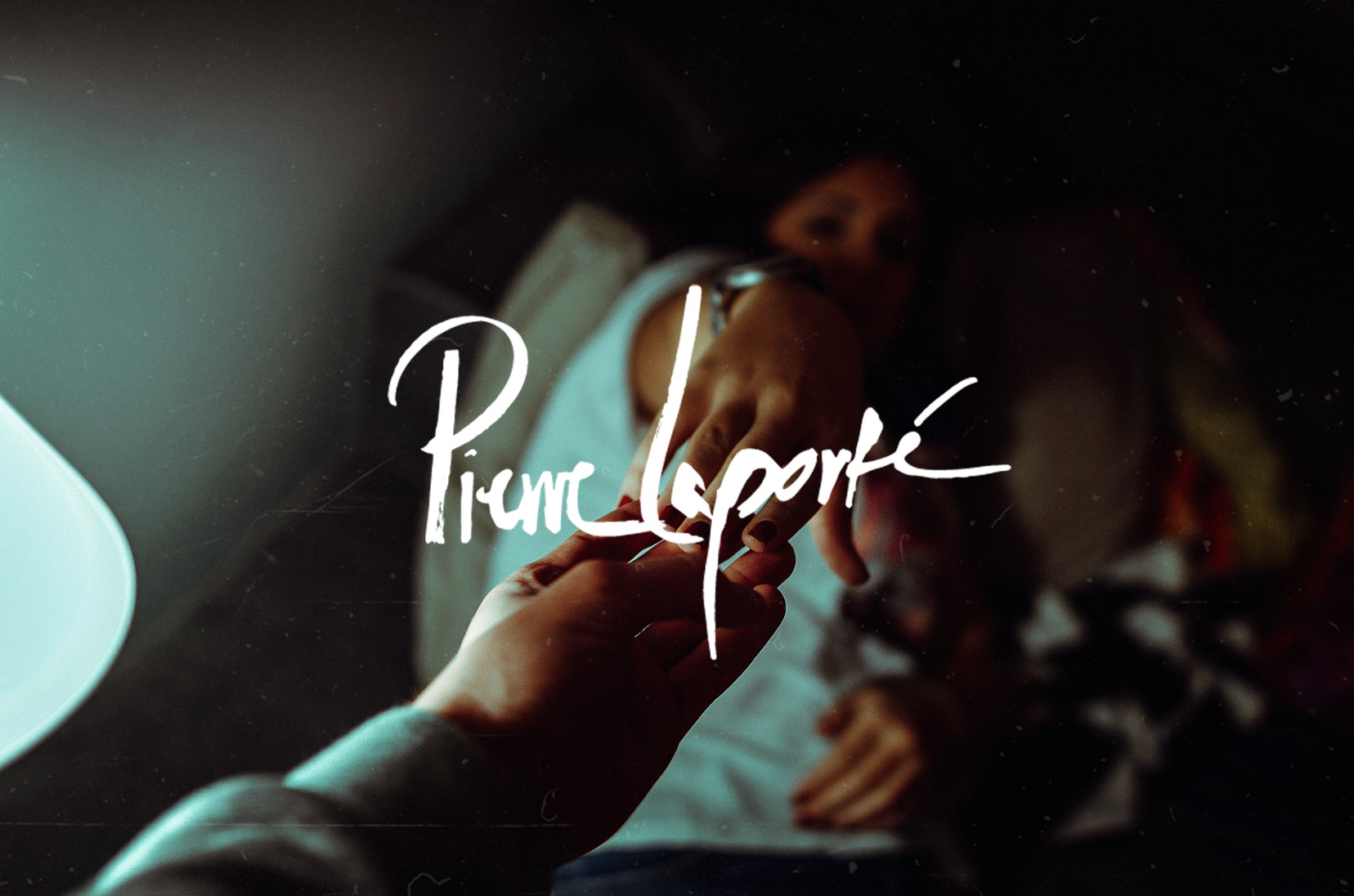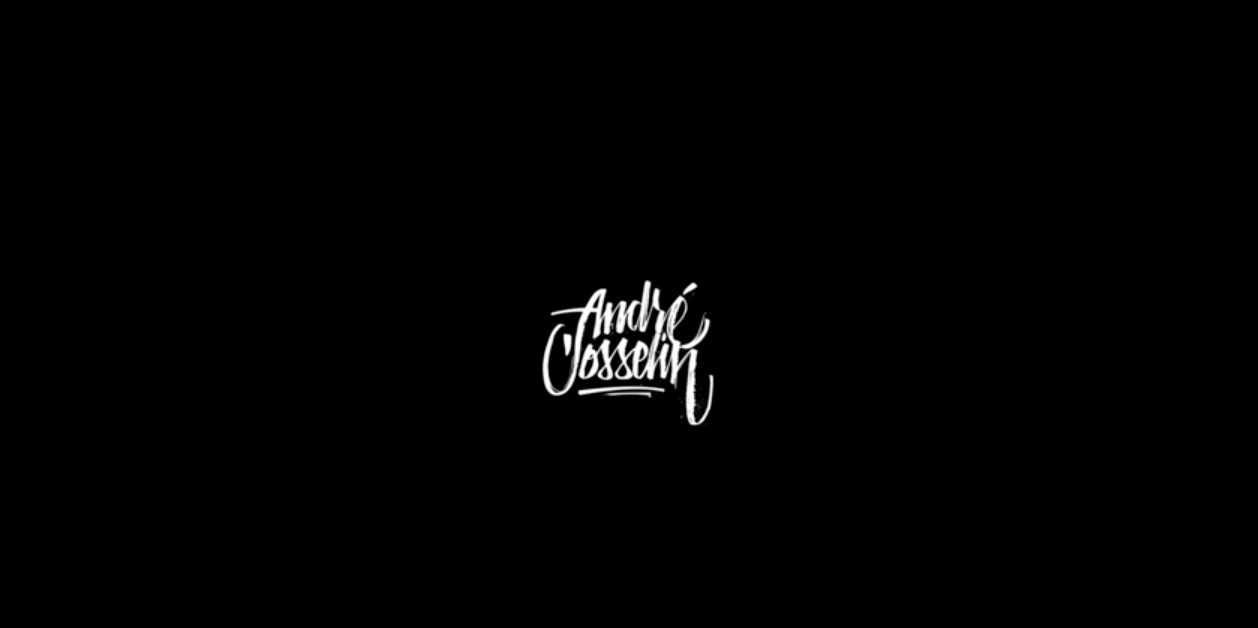
Wie nennt man diese Schriftart?
ich bin auf der Suche nach dem Namen dieser Schriftarten.
Falls sie niemand erkennen sollte, würde ich mich auch über ähnliche Schriftarten freuen. :)
vor 9 Minuten schrieb Ralf Herrmann:
Man nennt sie Handschrift oder Kalligrafie. ;-)
Jede verschiedene Handschrift hat ja einen anderen Namen? :D
Aber eben nicht als Schriftnamen, wenn es das einfach nur handgeschrieben gibt, oder bezeichnest du deine Handschrift - sofern du überhaupt noch mit der Hand schreibst - als "Peter123 Regular"?
Nein, die normale Handschrift bezeichnet er als „Peter123 Kursive“. Die „Peter123 Regular“ sind nur die Druckbuchstaben, außer wenn er sie mit Edding schreibt, dann ist es nämlich die „Peter123 Bold“:nicken:
Nun, ich hatte einmal einen lieben Kollegen, ja, damals auch Vorgesetzter. Er heiße Dietrich Wendel, und der schrieb (ich hoffe er schreibt noch) in einer derart sauberen eigenen "Normschrift" mit der er eben nicht nur extrem sauber technische Zeichnungen beschriftete, sondern auch längere Texte sehr rasch zu Papier brachte. Es sah förmlich aus, als hätte er einen digitalen Plotter in der Hand, und hätte ich noch ein Schriftmuster von ihm (wobei ich sehr bedauere, das nicht zu haben) und würde das hier einstellen, würde mit Sicherheit jeder hier die Verwendung eines Fonts vermuten - selbst ich, so ebenmäßig war seine Handschrift. Ich habe gelegentlich Beschriftungen auf Transparenzpapier übereinander gelegt, und mich gewundert, wie ein Mensch das derart deckungsgleich hin bekommt. Leider war das ganz am Anfang meiner Schriften-.Bastelei mit Corel 1.2, und die Handscanner dieser Zeit waren einfach noch zu fast nichts zu gebrauchen.
Und ja, hätte ich noch Texte von ihm, hätte ich bestimmt schon längst danach die Wendel Normal digitalisiert.